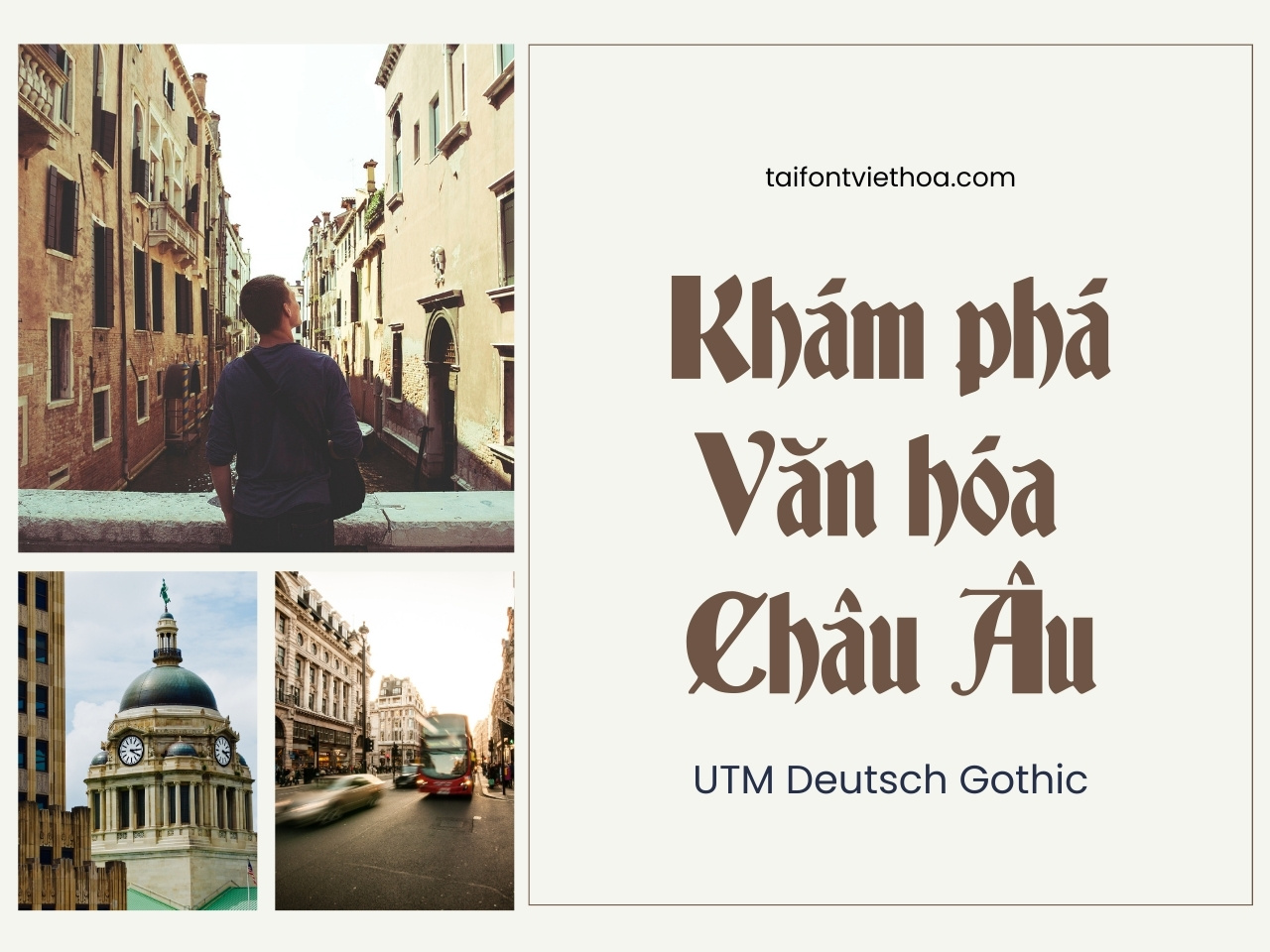
Giới thiệu về font UTM Deutsch Gothic
UTM Deutsch Gothic là phiên bản Việt hóa của font Deutsch Gothic – một kiểu chữ gothic cổ điển, mang phong cách mạnh mẽ và đậm chất lịch sử châu Âu thời trung cổ. Font gốc nổi bật với các nét chữ sắc nét, góc cạnh và hoa văn đặc trưng, tạo nên vẻ uy nghiêm và bí ẩn. Phiên bản Việt hóa đã được hoàn thiện để hỗ trợ đầy đủ tiếng Việt cùng hơn 100 ngôn ngữ khác, giúp mở rộng khả năng ứng dụng trong các dự án thiết kế nghệ thuật và lịch sử.
Font UTM Deutsch Gothic được taifontviethoa.com sưu tầm và chọn lọc kỹ càng nhằm phục vụ cộng đồng thiết kế Việt Nam. Phiên bản Việt hóa giữ nguyên tinh thần cổ điển và mạnh mẽ của bản gốc, đồng thời tối ưu khả năng hiển thị tiếng Việt, rất phù hợp cho các dự án branding, poster nghệ thuật và truyền thông mang phong cách lịch sử.
Đặc điểm thiết kế và ứng dụng của UTM Deutsch Gothic
UTM Deutsch Gothic sở hữu cấu trúc gothic với các nét chữ sắc nét, góc cạnh và hoa văn trang trí phức tạp. Font có thiết kế đậm nét, dễ nhận diện và tạo hiệu ứng thị giác ấn tượng, rất phù hợp cho tiêu đề, logo và các thiết kế cần sự khác biệt và mạnh mẽ. Font được tối ưu để đảm bảo tính dễ đọc trên nhiều kích thước và môi trường sử dụng khác nhau.
Font phù hợp sử dụng trong thiết kế poster, bảng hiệu, quảng cáo, nhận diện thương hiệu và các dự án truyền thông nghệ thuật. Các ngành nghề phù hợp gồm: nghệ thuật, lịch sử, giải trí, thời trang và truyền thông sáng tạo.